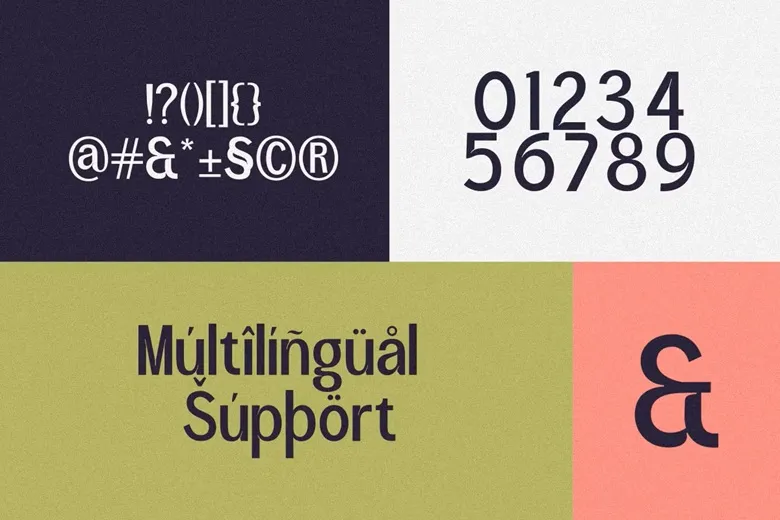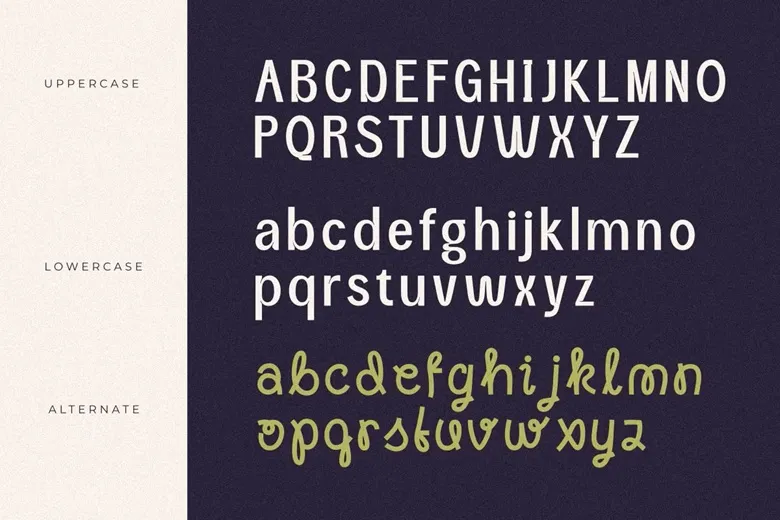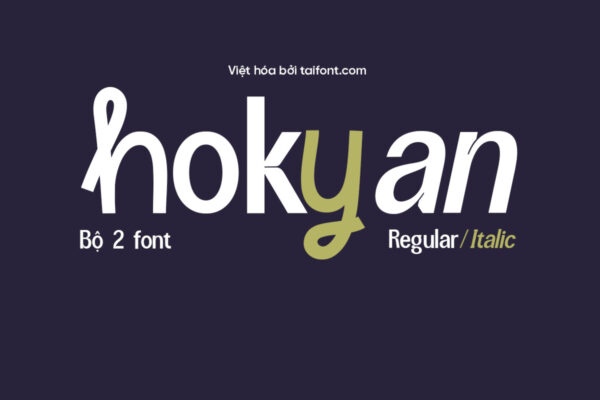
Giới thiệu về Font TF Hokyan Regular & Italic Việt hóa
TF Hokyan Regular & Italic Việt hóa là một bộ font chữ không chân (sans-serif) nổi bật với thiết kế thanh lịch, hiện đại và đầy sang trọng. Với hai phiên bản Regular (thẳng) và Italic (nghiêng), bộ font này mang đến sự linh hoạt trong việc thể hiện thông điệp, toát lên phong thái chuyên nghiệp, tinh tế và đẳng cấp, lý tưởng cho mọi ấn phẩm cần sự rõ ràng và cuốn hút.
Với đặc điểm là nét không chân gọn gàng, tính thẩm mỹ cao và khả năng ứng dụng đa dạng, Hokyan là lựa chọn hoàn hảo cho các thiết kế muốn truyền tải sự hiện đại, sang trọng và chuyên nghiệp, đặc biệt là trong lĩnh vực in ấn:
- In ấn cao cấp: Hoàn hảo cho các ấn phẩm in ấn đòi hỏi sự tinh tế và chất lượng cao như tạp chí, sách, brochure, catalogue, thiệp mời, bao bì sản phẩm cao cấp, hoặc danh thiếp. Độ rõ ràng và sắc nét của font giúp nội dung dễ đọc ngay cả trên giấy, đồng thời mang lại vẻ ngoài chuyên nghiệp và sang trọng.
- Tiêu đề và phụ đề: Phiên bản Regular rất phù hợp cho các tiêu đề chính (headline) và phụ đề cần sự mạnh mẽ, rõ ràng. Trong khi đó, phiên bản Italic mang lại vẻ mềm mại, bay bổng và tạo điểm nhấn tinh tế cho các lời dẫn, trích dẫn, hoặc các đoạn nhấn mạnh.
- Thiết kế nhận diện thương hiệu: Lý tưởng cho logo, tagline hoặc bộ nhận diện thương hiệu của các công ty, doanh nghiệp muốn truyền tải sự hiện đại, uy tín và sự thanh lịch. Hokyan giúp xây dựng một hình ảnh thương hiệu vững chắc và dễ nhận diện.
- Website và ứng dụng: Tuy là font in ấn, Hokyan cũng rất phù hợp cho giao diện người dùng trên website hoặc ứng dụng, mang lại trải nghiệm đọc mượt mà và chuyên nghiệp.
Với TF Hokyan Regular & Italic Việt hóa, bạn có thể dễ dàng thổi hồn tinh tế, sang trọng và vẻ đẹp hiện đại vào các thiết kế, tạo ra những sản phẩm không chỉ đẹp mắt mà còn đầy cảm xúc và sức hút đặc biệt.